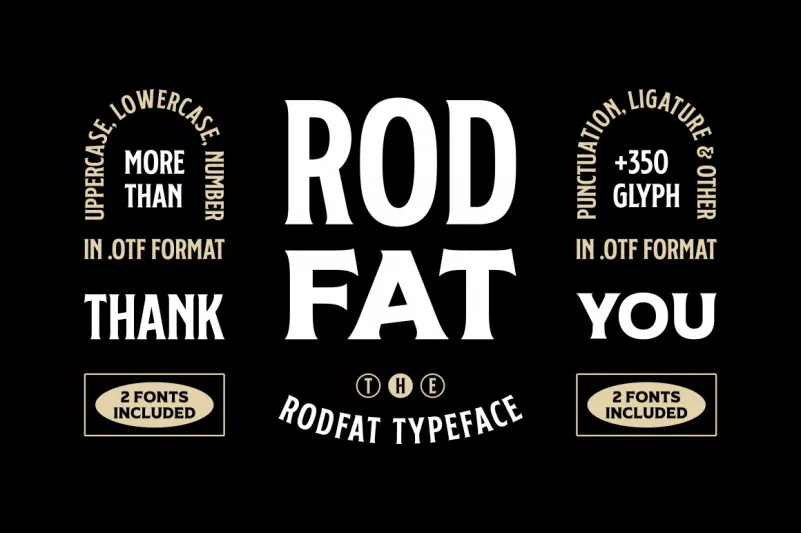
Rodfat Display Font
A C00zona apresenta a Rodfat Display Font, uma nova tipografia para uso impresso que combina perfeitamente com vários projetos modernos e vintage. Este tipo de fonte é perfeito para aqueles buscando um equilíbrio harmonioso entre formas suaves e peso médio. Inspirada na Revolução Industrial, a Rodfat exala um toque nostálgico do início dos anos 20, oferecendo uma aparição moderna de um estilo clássico e delicado. Esta coleção está disponível em dois estilos: One e Two. É possível combinar os dois com sucesso, criando um visual único e sofisticado. Introduzindo a Rodfat Font pode revitalizar qualquer projeto, transportando-o ao passado, para aqueles tempos nostálgicos de início do século XX. Para quem busca uma fonte que se mistura perfeitamente em projetos atuais e vintage, essa é uma ótima escolha. A C00zona continua a expandir seu catálogo com cada lançamento, sempre buscando oferecer um novo gosto para os designers digitais e impressores do mundo todo.